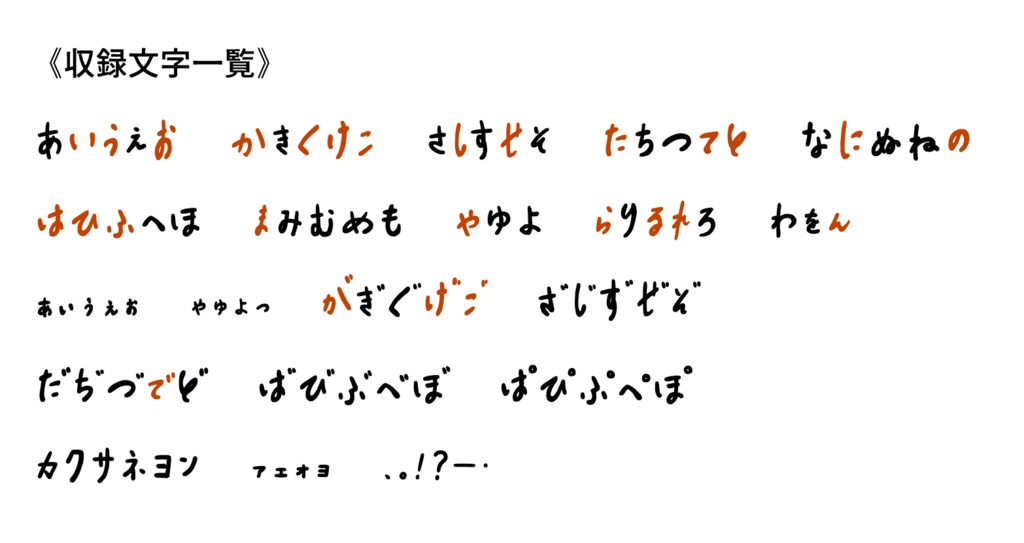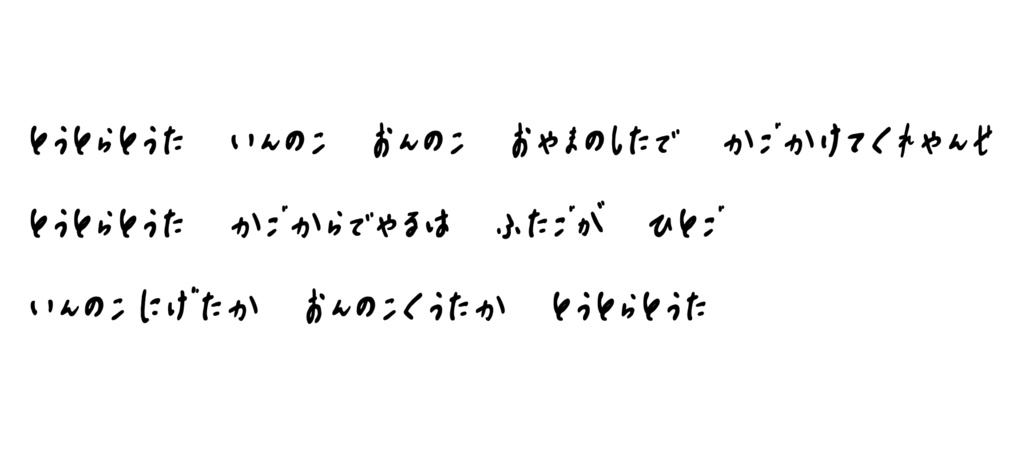
とうとらフォント
【概要】
作中で真宮寺が「かごのこ」の儀式のために書き起こした歌詞メモをもとにした、半イメージフォント*です。 *収録文字一覧表(画像2枚目)のうち、赤字の文字は実際の書体に寄せて作成。それ以外の文字はイメージ書体です。
【収録内容】
ひらがな81文字(清音、濁音、半濁音、小書き) カタカナ10文字(カ,ク,サ,ネ,ヨ,ン,ァ,ェ,ォ,ョ) 記号6文字(、,。,!,?,ー,・)